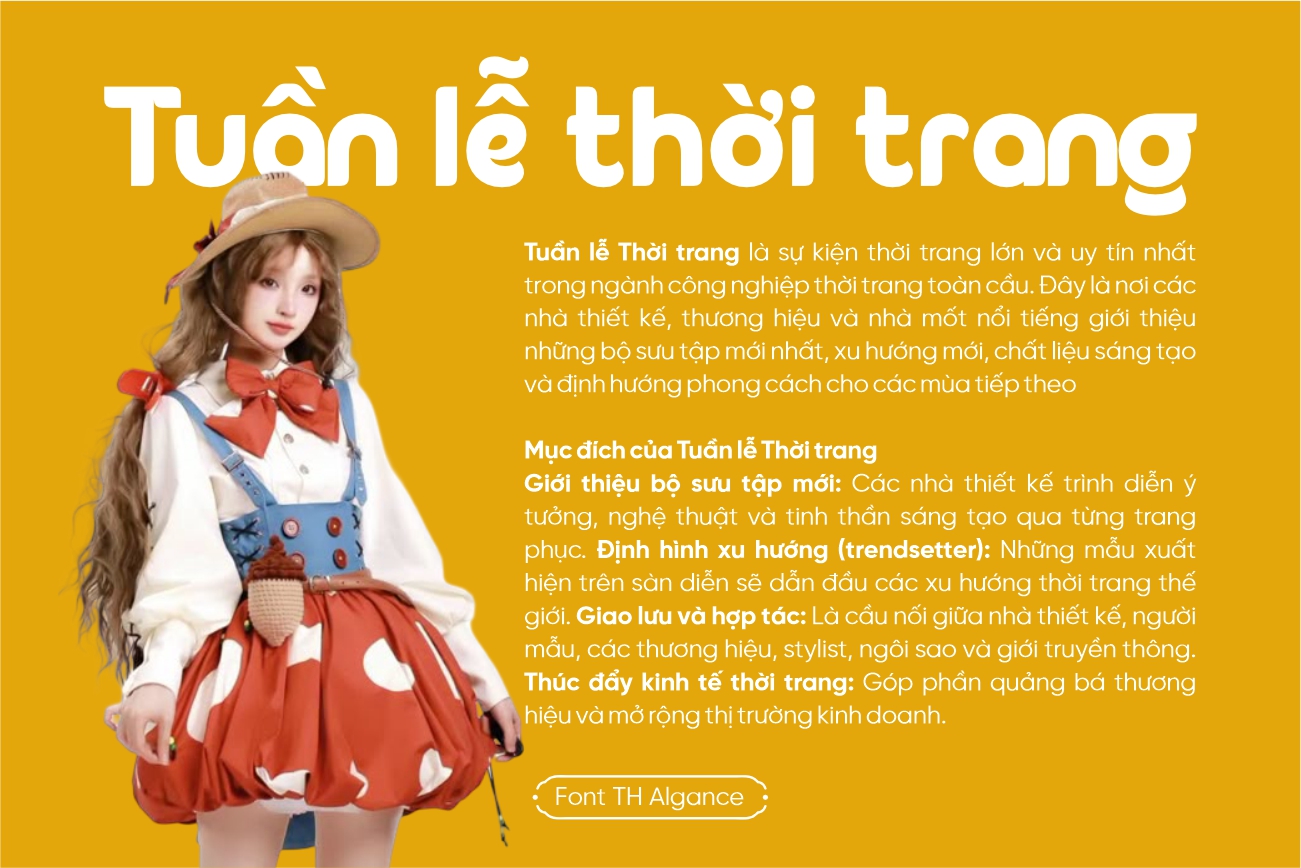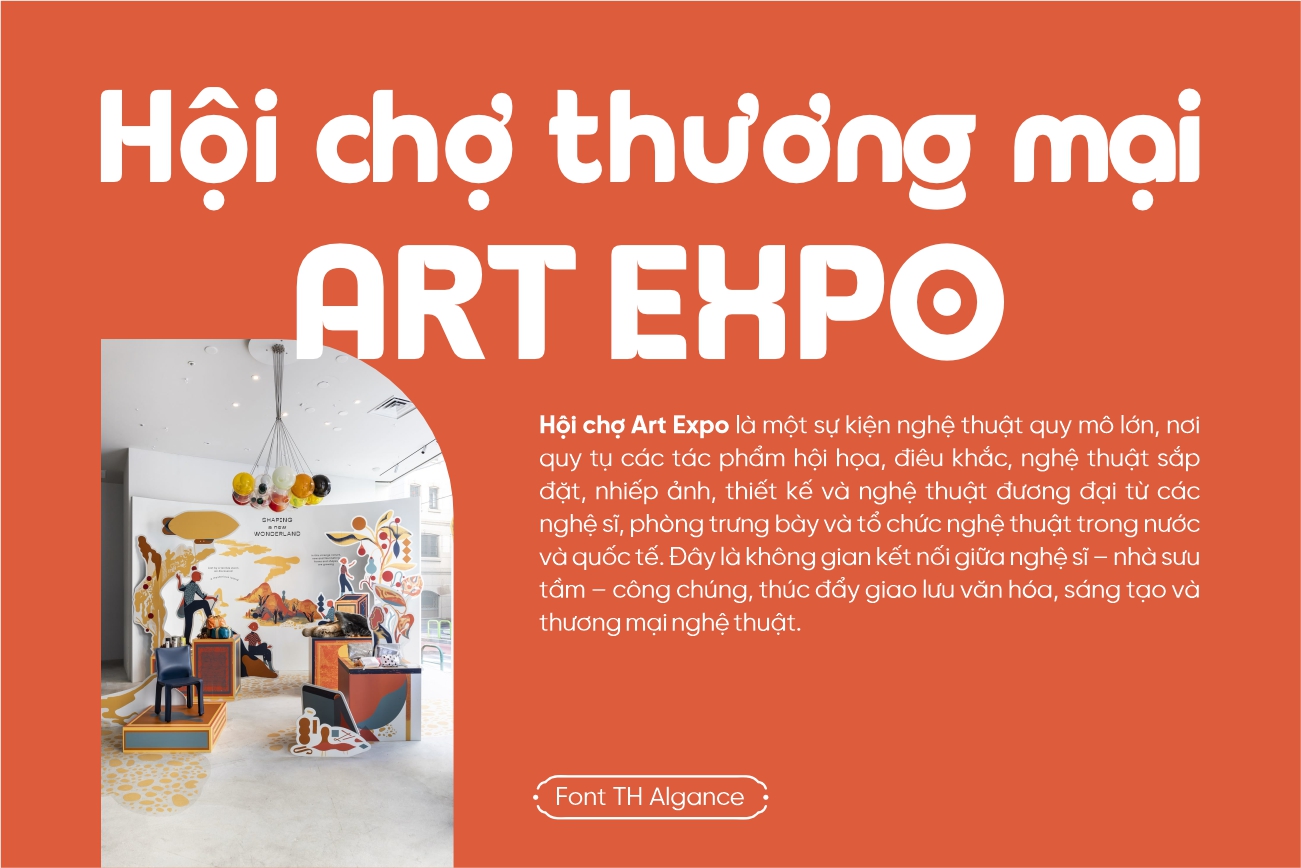
Font Chữ Sans Serif Hiện Đại Cho Thiết Kế Tối Giản - TH Algance Việt Hóa
Tác giả Rantautype Studio
Trong xu hướng thiết kế đồ họa đương đại, việc tìm kiếm một font chữ Sans Serif vừa mang nét sang trọng, vừa đảm bảo tính hiện đại là ưu tiên hàng đầu của các Designer chuyên nghiệp. Algance - Modern Sans Serif chính là câu trả lời hoàn hảo cho bài toán đó. Đặc biệt hơn, phiên bản này đã được Team TH Việt hóa hoàn chỉnh, giải quyết triệt để vấn đề lỗi dấu, giúp cộng đồng sáng tạo tại Việt Nam thỏa sức ứng dụng mà không gặp bất kỳ trở ngại ngữ pháp nào.
Algance không chỉ đơn thuần là một bộ phông chữ, mà là bản giao hưởng tinh tế giữa các đường nét hình học gọn gàng và sự mềm mại đầy tính nghệ thuật. Được định hình là một font chữ tối giản, Algance loại bỏ hoàn toàn những chi tiết rườm rà ở phần chân chữ, tập trung tối đa vào trải nghiệm đọc mượt mà và vẻ đẹp thanh lịch vượt thời gian. Sự cân đối trong độ dày của từng nét (stroke) giúp Algance trở nên nổi bật và dễ đọc, dù được sử dụng ở kích thước tiêu đề lớn hay văn bản nội dung.
Điểm sáng giá nhất của phiên bản do Team TH thực hiện chính là sự tỉ mỉ trong từng dấu câu tiếng Việt. Các dấu mũ, dấu ngã, dấu hỏi đều được cân chỉnh khoảng cách (kerning) kỹ lưỡng, đảm bảo sự hài hòa tổng thể khi gõ các văn bản dài. Nhờ đó, Algance trở thành lựa chọn lý tưởng cho các dự án xây dựng nhận diện thương hiệu (branding), thiết kế logo cao cấp, bìa tạp chí thời trang hay các bao bì mỹ phẩm cần sự sang trọng.
Nếu bạn đang theo đuổi phong cách font chữ tối giản cho các ấn phẩm truyền thông, thiệp cưới hay giao diện website (UI/UX) cần sự thoáng đãng, Algance Việt hóa chắc chắn sẽ nâng tầm thiết kế của bạn lên một đẳng cấp mới. Đây là minh chứng rõ ràng nhất cho thấy sức mạnh của một font chữ Sans Serif chất lượng có thể thay đổi hoàn toàn diện mạo của một tác phẩm nghệ thuật.
TH Algance